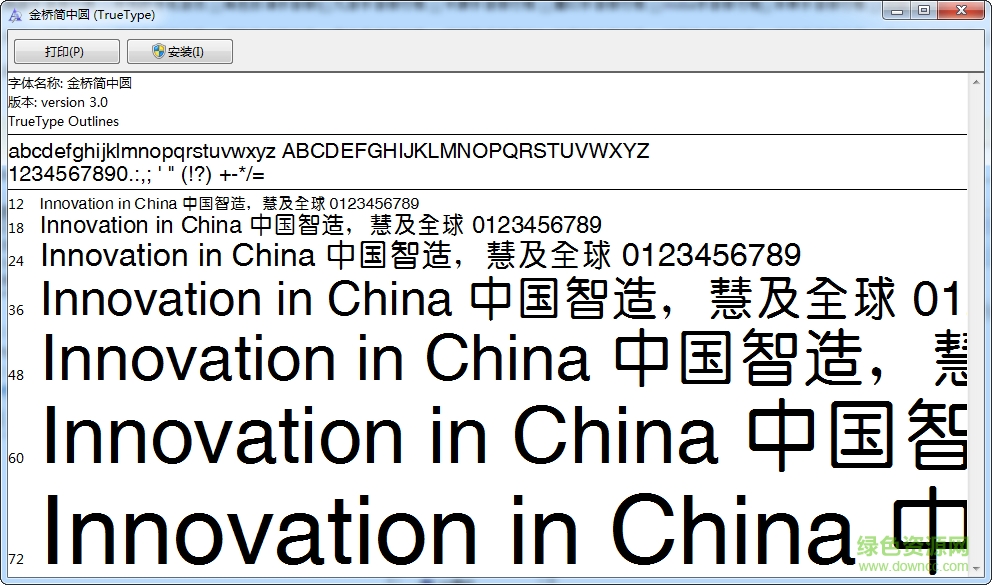
jqzhongyuanjt
jqzhongyuanjt字體是一款圓潤的金橋字體,風(fēng)格典雅,筆畫流暢,結(jié)構(gòu)飽滿,非常實用,用作印刷、排版、平面設(shè)計等領(lǐng)域都可以,非常使用進(jìn)行平面廣告詞設(shè)計的朋友使用,需要的用戶就請登陸綠色資源網(wǎng)進(jìn)行下載安裝吧!